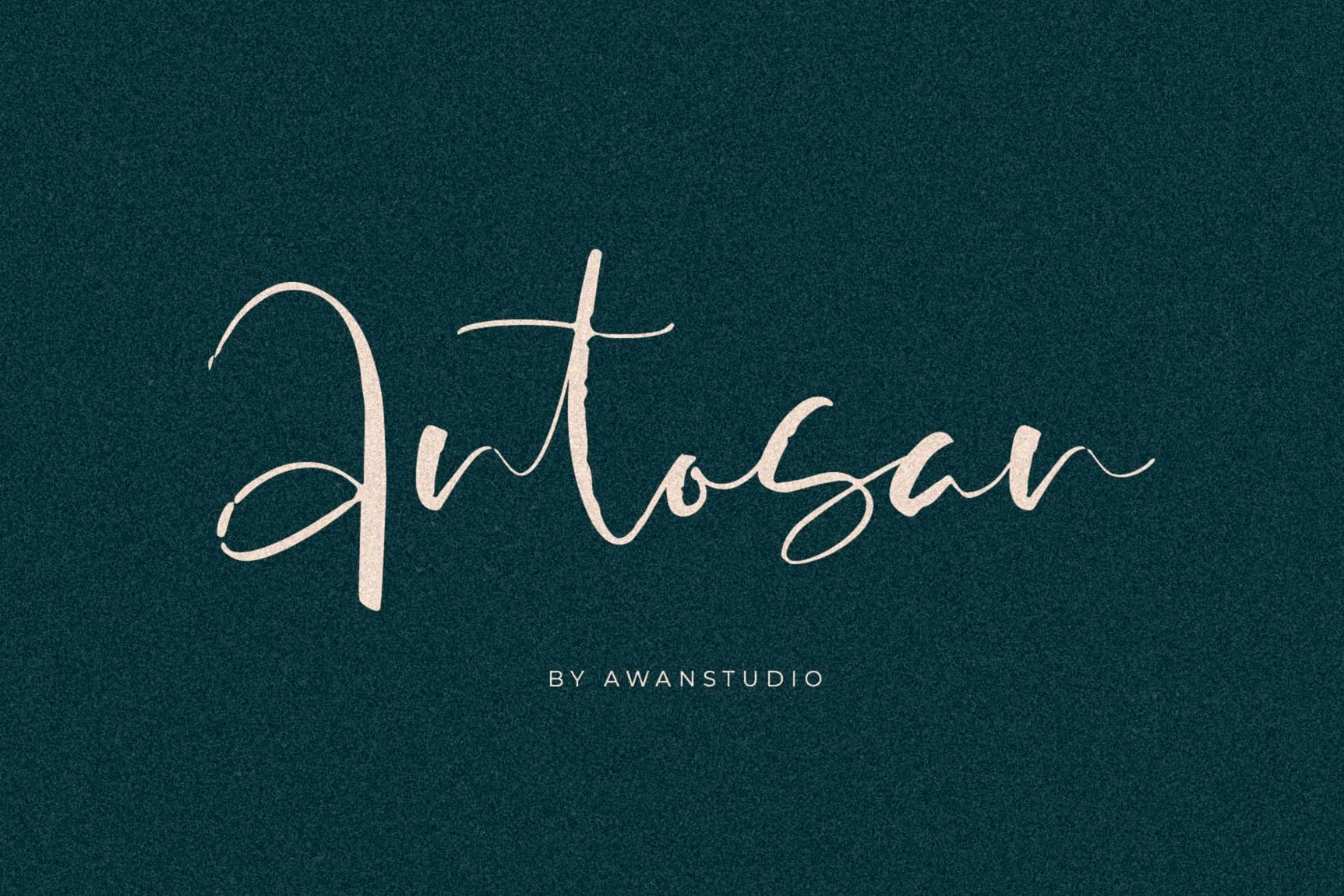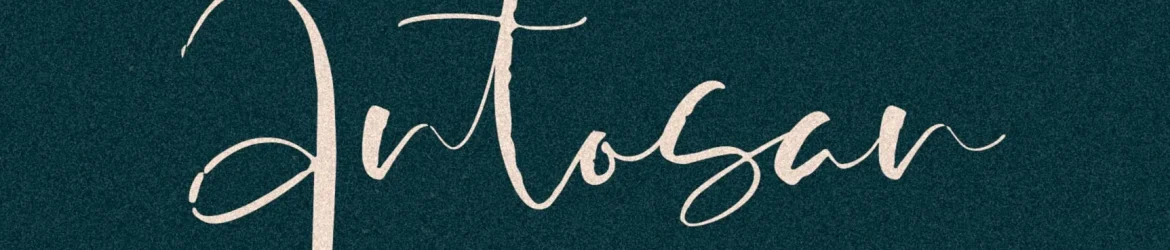
Antosan Script Font – Download Grátis
A Antosan Font é uma elegante escolha para designers que desejam adicionar um toque autêntico e único a suas criações digitais. Esta fonte escrita à mão oferece características realistas, perfeitas para criar designs incríveis de uma forma fácil e instantânea. Desenvolvida pelo estúdio awan studio, esta font se tornou a escolha perfeita para um amplo espectro de aplicativos, incluindo logotipos, citações, embalagens de produtos, letras personalizadas, cartões de visita, convites e materiais promocionais. Seja você um criador de marca ou artista gráfico, a Antosan Font é uma excelente opção para dar vida à sua ideia única de maneira elegante e autêntica.